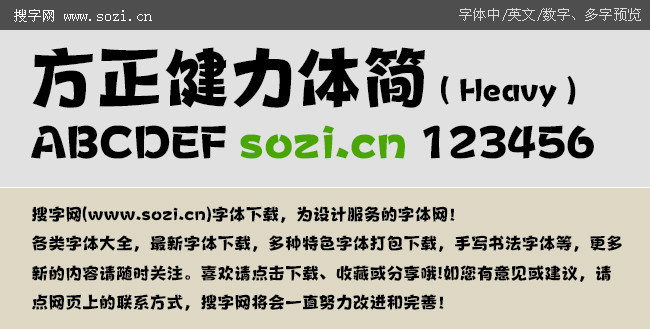
方正健力體簡Heavy
搜字網(wǎng)提供一款方正健力體簡中文字體下載,方正健力體是作者從某健身的標志引發(fā)的靈感,點,撇,捺,抅,橫,直劃等都是不同方向,也好像各種健身項目的不同表達方式一樣,是一款充滿動感和活力的字體。適合健美行業(yè),活力飲料,運動服裝和運動鞋的廣告宣傳。
• 風格類別: 現(xiàn)代藝術體